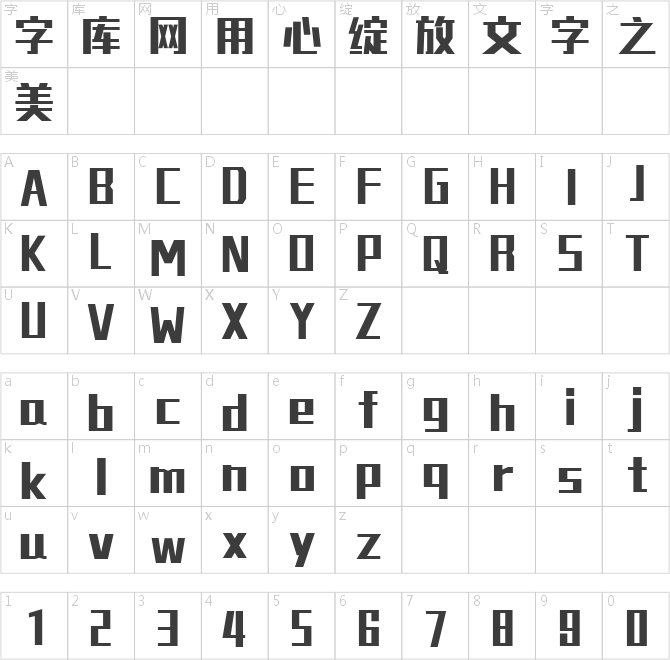
銳字工房金剛粗黑簡1.0 詳情頁
字體名稱: 銳字工房金剛粗
銳字工房金剛粗黑簡1.0
銳字工房金剛粗黑簡1.0字體字庫是一款讓人賞心悅目、百看不厭的中文字體,適合各類廣告和產(chǎn)品包裝設(shè)計應(yīng)用,字體大小3.17MB,格式為ttf字體,上傳用戶是afig,作者/版權(quán)方為銳字潮牌